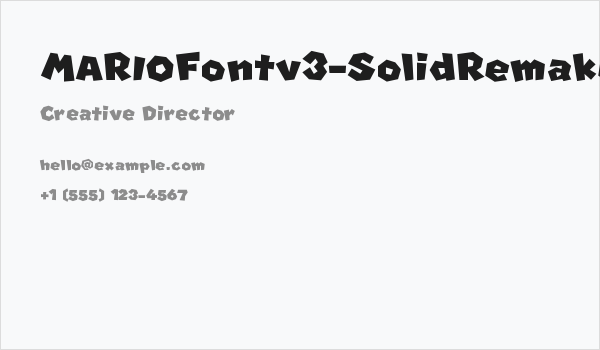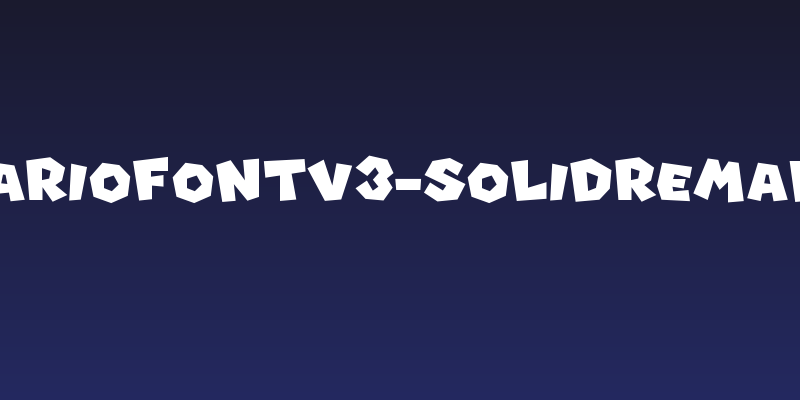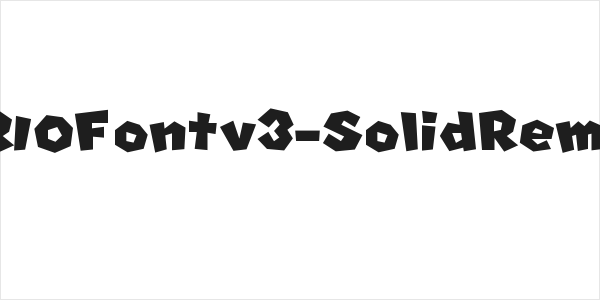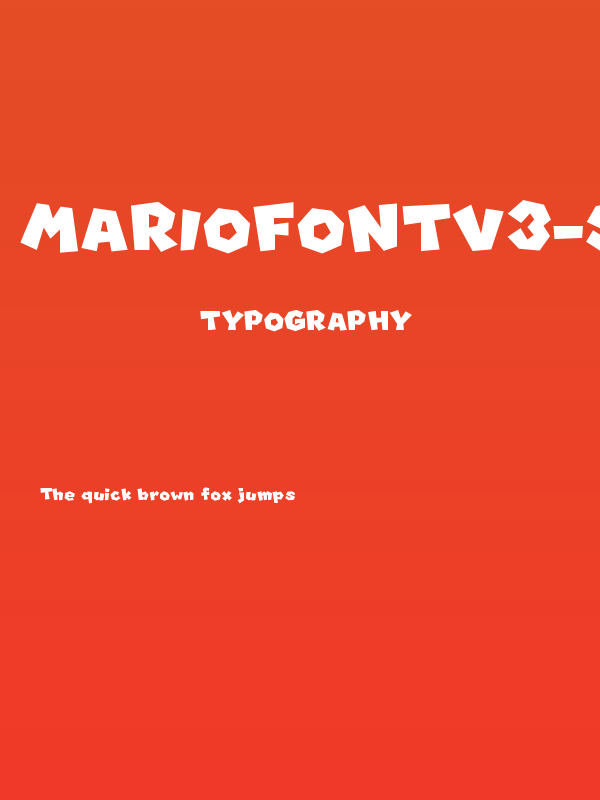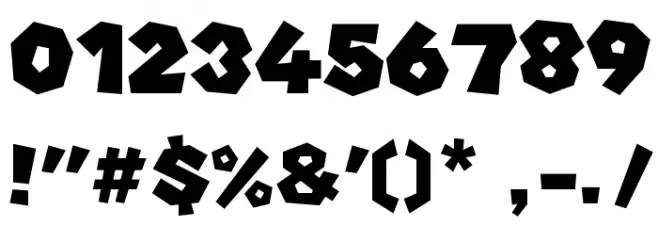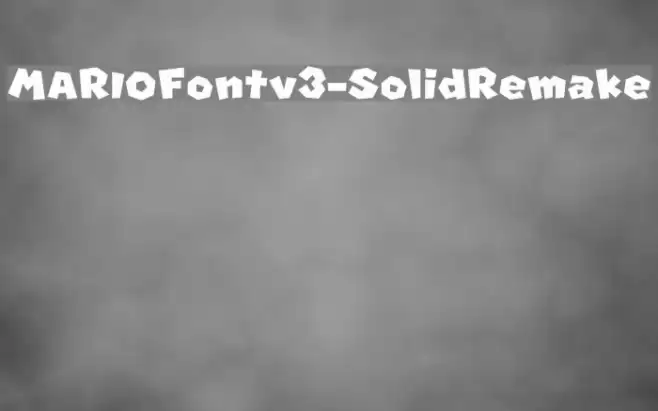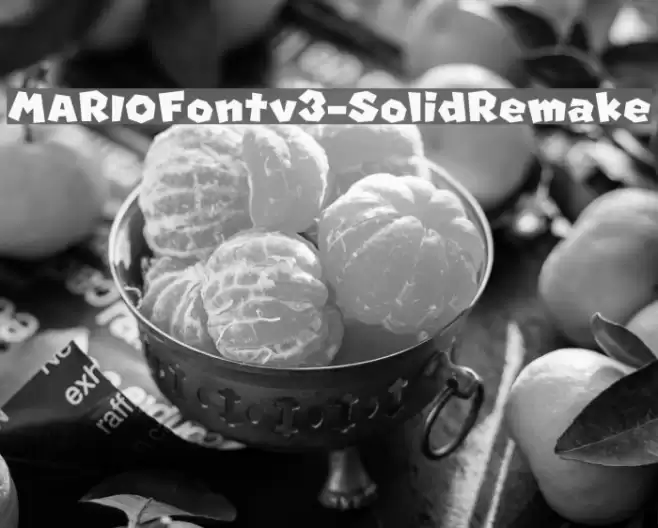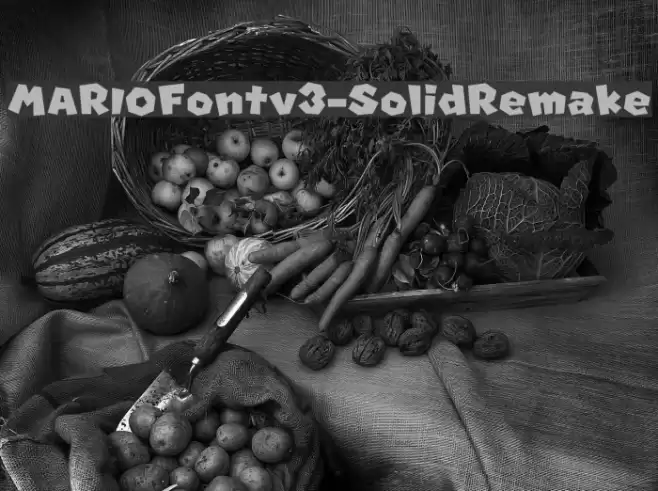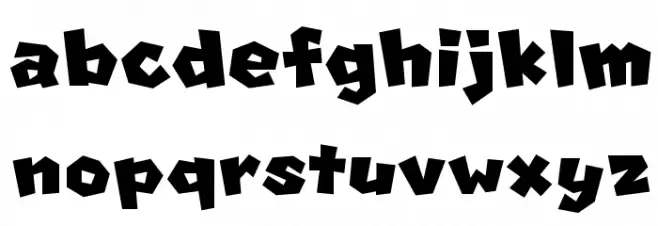
MARIOFontv3-SolidRemake Font
| 全体的なスタイル | Playful, Energetic, Geometric |
| おすすめプロジェクト | Ideal for video game titles, children's book covers, posters, and any project requiring a fun and bold aesthetic. |